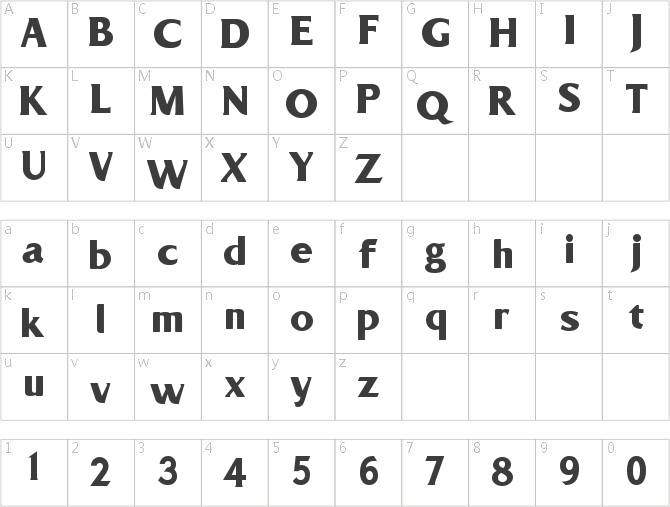
字体名称: Upward
Upward Bold
Upward Bold字体下载华司向上体
Upward Bold字体华司向上体字库是一款让人赏心悦目、百看不厌的英文字体,适合各类广告和产品包装设计应用,字体大小0.04MB,格式为ttf字体,上传用户是堂哥,作者/版权方为沃赛商业(海南)有限公司